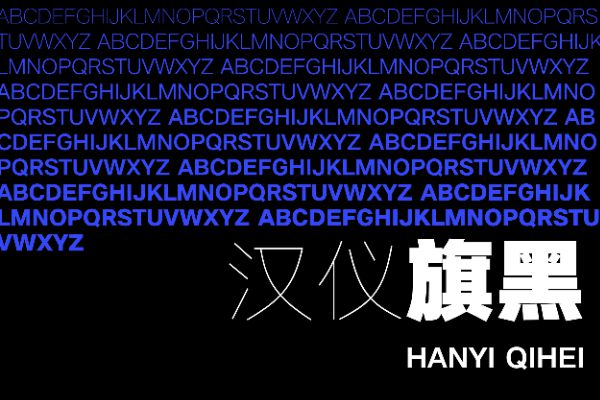
汉仪旗黑 60S
汉仪旗黑拥有15种不同的字重,是有史以来字重最全的一款黑体。同时,汉仪旗黑字体的设计,简约、爽朗,富有时代气息。汉仪旗黑还特别注重汉字的民族性和传统文化,在笔划设计中融入了书写的韵味,采用 “ 阴阳”线的处理方法,让字体的线条变得细腻考究,使笔划更加挺拔有力,刚柔相济。
齐立
1984年以优异的成绩(美术字第一名)考入上海印刷技术研究所字体研究室,专职从事字体设计工作。从2003年到2012年担任方正电子字模团队任高级字体设计师,创作了方正倩体系列、方正胖娃、方正稚艺、方正剪纸、 方正兰亭宋、微软雅黑(屏幕显示字体)、方正兰亭黑系列、标题用超细黑、方正黑隶系列、方正俊黑系列字体等优秀字体。2012年至今,齐立老师担任汉仪签约设计师,创作的汉仪旗黑,是有史以来字重最全的一款黑体。
齐立